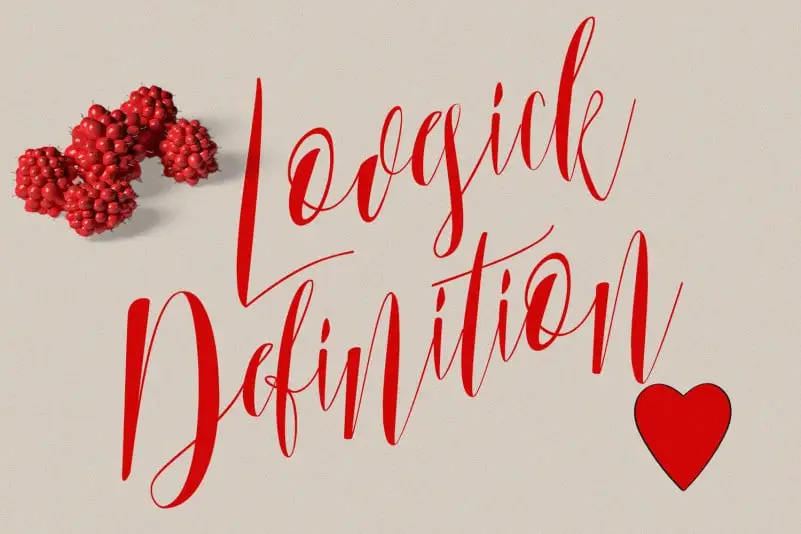
Lovesick Definition Font – Download Grátis
A fonte ‘Lovesick Definition’ é uma escolha perfeita para designers que buscam um estilo moderno e sofisticado na mistura do calligrafia casual, com um toque de elegância. Seja para criar identidades visuais, cartas de casamento ou até mesmo rótulos de vinho, esta fonte é ideal. Perfeita tanto para trabalhos criativos quanto para aplicar em uma variedade de formatos: rótulos de embalagens, carteirinhas de negócio, assinaturas e até mesmo capas de livros. Além disso, seu uso pode ser visto em cartazes, mídia social, adesivos e revistas. A fonte ‘Lovesick Definition’ é o toque final perfeito para qualquer projeto que deseje trazer a personalidade da escrita à vida do design gráfico.